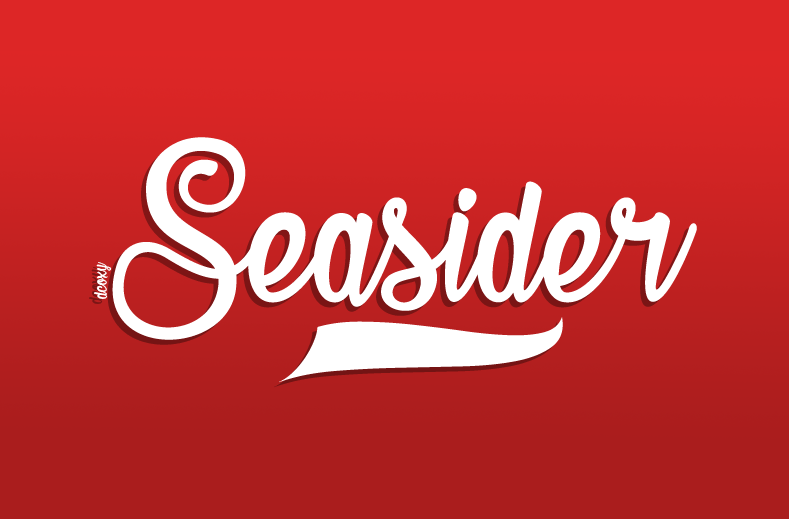
Seasider Font – Download Grátis
Se você está procurando por uma fonte para dar vida à suas criações digitais com um toque autêntico e elegante, o ‘Seasider Font’ é a solução perfeita. Essa fonte escrita a mão de categoria Handwritten oferece nuances sutis que ajudam qualquer projeto a se destacar. Seja em uma carta pessoal ou uma campanha publicitária, ela vai fazer seu trabalho. Como designer, você adorará o grau do controle e precisão que dá sua obra à vida através dessa fonte. A qualidade de suas criações ficará ainda mais impressionante ao utilizar esta fonte escrita a mão. O ‘Seasider Font’ foi criado por Greg Medina com inspiração nas paisagens costeiras, proporcionando um toque natural e acolhedor que é essencial para muitos projetos. As letras têm uma sensação de fluididade e flexibilidade, permitindo que você faça ajustes sutis para personalizar seu texto. Se você está procurando por uma fonte escrita a mão perfeita para qualquer tipo de projeto visual, considere o ‘Seasider Font’. Sua versatilidade e detalhes cuidadosos fazem dele um grande investimento que garantirá sucesso em seus trabalhos digitais. Para adquirir sua licença, entre em contato comigo antes: